캘리그라피는 단순히 글씨를 예쁘게 쓰는 걸 넘어서, 내 마음을 담아 표현할 수 있는 소중한 예술이에요. 처음에는 단어 하나 제대로 쓰는 것도 어려웠지만, 시간이 지나면서 내가 쓰는 글씨에 감정이 묻어나는 걸 느끼게 되었어요. 글씨를 쓰는 시간은 마치 명상 같고, 하루의 스트레스를 비워내는 힐링의 순간이 되었답니다.
내가 생각했을 때 캘리그라피는 글씨 이상의 가치를 줘요. 감성적인 표현을 넘어, 나 자신을 다시 바라보게 해주고, 주변 사람들과도 더 따뜻하게 소통할 수 있는 힘을 준답니다. 지금부터 제가 캘리그라피를 배우고 직접 겪은 5가지 변화를 소개할게요!
🎨 창의력과 감성 표현력 향상
창의력과 감성 표현력 향상
처음에는 캘리그라피를 그저 예쁜 글씨체라고 생각했어요. 하지만 글자를 하나하나 디자인하고 구성하다 보면 나만의 스타일을 고민하게 되면서 자연스럽게 창의력이 자라나요. 어떤 단어를 어떻게 표현할지, 색상과 구조는 어떻게 조합할지 매 순간 상상력을 자극해요.예를 들어, '사랑'이라는 단어를 쓸 때는 곡선이 많고 부드러운 느낌을 살리고 싶어서 붓펜의 각도와 힘을 조절하게 돼요. 반대로 '도전'이라는 단어는 강렬하고 직선적인 느낌으로 써야 하니 전혀 다른 표현법을 사용하게 되죠. 단어 하나에도 감정을 담다 보니 글자가 그림처럼 느껴지기도 해요.
감성도 함께 자라나요. 글을 쓰다 보면 자연스럽게 감정을 들여다보게 돼요. 무심코 흘려보내던 하루의 느낌, 문장 하나에 담긴 내 속마음을 글자에 투영하는 거죠. 그래서 캘리그라피는 내면을 표현하는 또 다른 언어 같아요.
어느새 나만의 손글씨가 만들어지고, 그 글씨가 일기처럼 내 하루를 기록하는 도구가 돼요. 시각적인 창의성과 감성적인 공감력이 자연스럽게 발달하는 경험을 하게 되죠.
📌 감성 글귀 예시 비교표
글귀 표현 스타일 추천 색상 감정 키워드 사랑해 곡선, 붓글씨 분홍, 빨강 따뜻함, 설렘 힘내 굵은 획, 강조 파랑, 보라 응원, 용기 괜찮아 부드러운 흐름 초록, 회색 위로, 포근함 표현이 늘어갈수록 내 글귀에도 감정이 살아나요. 감성적인 단어에 맞는 분위기와 느낌을 직접 그리는 기분이에요. 🎨
🧘♀ 스트레스 해소와 마음의 안정
스트레스 해소와 마음의 안정 캘리그라피를 하면 마음이 편안해지는 걸 느낄 수 있어요. 붓이나 펜을 천천히 움직이면서 글씨를 써 내려가는 순간, 머릿속이 조용해지고 복잡한 생각들이 하나씩 정리되거든요. 마치 명상을 하는 것처럼 마음을 차분하게 해줘요.
일상에서 스트레스를 받을 일이 많잖아요. 그럴 때 종이 한 장, 펜 하나만 있으면 마음을 달래줄 수 있는 취미가 있다는 게 얼마나 큰 위안인지 몰라요. 감정이 격해질수록 글씨에도 그 느낌이 묻어나는데, 그걸 그대로 표현해내면 오히려 후련함이 밀려오죠.
특히 아날로그적인 손글씨는 디지털 화면과는 전혀 다른 감성을 전달해줘요. 손끝으로 느껴지는 감촉, 잉크의 번짐, 종이의 질감까지 모든 게 위로가 돼요. 혼자만의 시간을 가지며 자신을 돌아보는 소중한 루틴이 된답니다.
글씨를 쓰는 과정에서 호흡이 느려지고, 몸의 긴장도 풀리면서 자연스럽게 심신이 안정돼요. 하루 중에 마음을 비우는 시간이 생기니까 삶의 균형도 맞춰지는 느낌이에요.
🧘 캘리그라피 효과 비교표
효과 내용 지속성 개선 사례 스트레스 해소 감정 표현으로 마음이 가벼워짐 꾸준히 유지됨 불면증 완화 자기 위로 글귀로 스스로를 다독임 장기적 효과 자존감 상승 집중 호흡 호흡을 조절하며 집중 즉각적 효과 불안감 감소 이런 효과 덕분에 많은 사람들이 요즘 ‘힐링 타임’으로 캘리그라피를 즐겨요. 하루에 10분만 해도 달라지는 걸 느낄 수 있답니다.
🧘 집중력과 인내심 기르기
집중력과 인내심 기르기
캘리그라피는 단순히 글씨를 따라 쓰는 게 아니에요. 한 획, 한 글자에 온전히 집중해야 하죠. 글씨 하나에 생각과 감정을 담는 과정에서 자연스럽게 집중력이 생겨요. 특히 조용한 공간에서 정해진 시간 동안 몰입해서 글씨를 쓰면, 짧은 명상과도 같아요.자신의 손과 눈, 그리고 마음이 조화롭게 움직여야 해서 처음엔 실수도 많아요. 하지만 그런 실수마저 나만의 스타일로 받아들이는 연습이 되죠. 인내심이 필요하지만 그만큼 얻는 보람도 커요. 시간이 지날수록 실력이 오르고, 글씨에도 성격이 드러나기 시작해요.
처음에는 '왜 이렇게 어렵지?' 싶던 것도 반복하면서 익숙해져요. 틀려도 괜찮다고 생각하게 되고, 다시 천천히 시작하면 돼요. 그렇게 꾸준히 반복하는 습관이 생기면서 생활 전반에 긍정적인 변화가 생겨요.
특히 아이들에게도 캘리그라피는 집중력 훈련에 좋아요. 요즘처럼 스마트폰에 익숙한 시대에, 아날로그 방식으로 글씨를 쓰며 집중하는 경험은 아이들의 두뇌 활동에도 도움이 돼요.
🧠 집중력 향상 포인트
방법 설명 기대 효과 글씨 반복 연습 한 문장을 반복적으로 써보기 집중력 강화 라인 연습 수직선/곡선 등 기본 획 그리기 손의 감각 향상 조용한 환경 조성 소음 없는 공간에서 글씨 쓰기 몰입도 상승 캘리그라피를 통해 집중과 인내를 기르면, 일상 속 다양한 상황에서도 차분함을 유지할 수 있어요. 특히 예민한 성격을 가진 사람들에게 큰 도움이 된답니다!
💬 소통 능력과 관계 개선
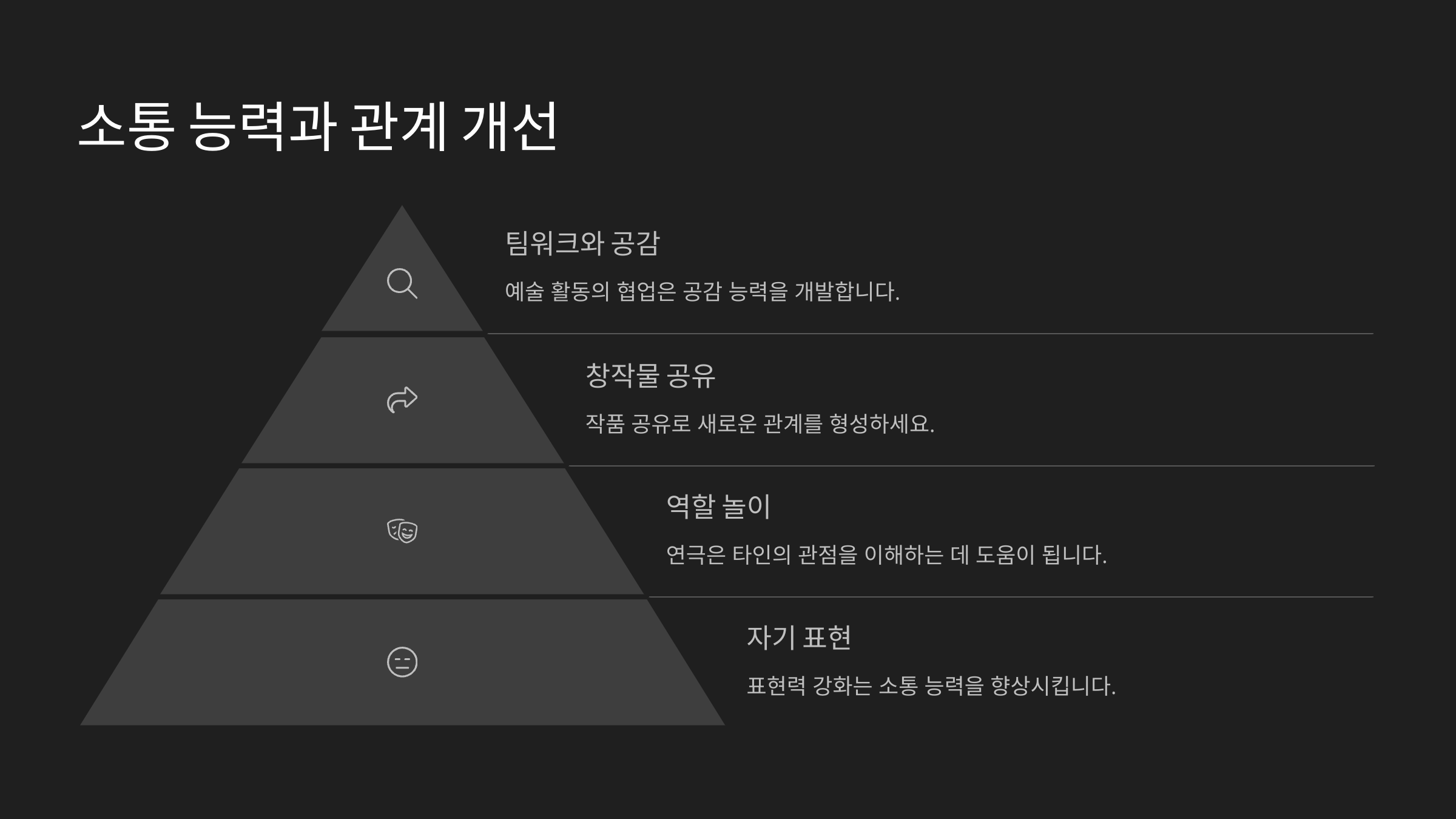
소통 능력과 관계 개선
디지털 메시지가 넘쳐나는 요즘, 손글씨로 전하는 메시지는 그 자체로 감동이에요. 제가 친구 생일에 손글씨로 편지를 써줬을 때, 받는 사람이 눈물까지 글썽였던 기억이 있어요. 그 사람을 생각하며 하나하나 정성스럽게 쓴 글씨는 진심이 고스란히 전해지거든요.직접 쓴 글귀는 사람과의 거리도 좁혀줘요. 예를 들어, 부모님께 '고마워요'라는 문장을 써서 작은 액자에 담아 드렸는데, 평소보다 훨씬 더 진심이 전해졌다고 하시더라고요. 캘리그라피는 마음을 시각적으로 표현하는 언어예요.
소셜미디어에도 자주 활용돼요. 직접 쓴 감성 문장을 사진과 함께 올리면 사람들과 감정적으로 소통할 수 있어요. 단순히 좋아요 수를 넘어서, 마음이 연결되는 순간들이 생겨요.
더불어 직장에서의 커뮤니케이션에도 활용할 수 있어요. 손글씨 메모나 작은 메시지 하나로 분위기를 따뜻하게 만들 수 있답니다. 감성은 디지털보다 오래 기억되는 법이니까요.
💌 감성 캘리그라피 사용 예
상황 사용 문장 전달 감정 받는 이 반응 생일 선물 "세상에 단 하나뿐인 너" 감동, 고마움 감격, 눈물 부모님 감사 "언제나 든든한 존재" 사랑, 존경 미소, 안도 퇴사 동료 "같이여서 행복했어요" 추억, 감사 감사 메시지 이처럼 손글씨는 단순한 표현을 넘어서, 사람의 마음을 움직이는 힘이 있어요. 진심을 담은 글씨가 관계를 더 가깝게 만들어준답니다. ✨
💼 취미를 넘어 수익으로
취미를 넘어 수익으로 처음엔 나를 위한 힐링으로 시작한 캘리그라피가 어느새 누군가에게 필요한 작업이 되기도 해요. 점점 실력이 늘다 보니 주변에서 부탁이 들어오기 시작했어요. 카드, 포스터, 현수막, 가게 간판까지 다양하게 활용되거든요.
요즘은 캘리그라피로 부업을 시작하는 사람들도 많아요. SNS에 작품을 올리거나, 온라인 클래스 플랫폼에서 강사로도 활동할 수 있어요. 또는 캘리그라피를 활용한 문구 제품을 직접 제작해 판매하기도 하죠.
특히 결혼식 초대장이나 기업 행사에도 손글씨가 큰 역할을 해요. 디지털 디자인과는 다른 ‘감성’이 있기 때문에 점점 수요도 높아지고 있어요. 자신만의 스타일이 확고해지면 브랜드화도 가능하답니다.
경제적 가치뿐만 아니라 성취감도 커요. 내가 쓴 글씨가 누군가에게 기쁨이 되고, 작품이 되어 누군가의 공간에 놓인다는 건 정말 뿌듯한 일이에요.
📈 캘리그라피 수익화 경로
수익 활동 설명 시작 방법 클래스 운영 취미 강좌나 원데이 클래스 SNS 홍보 + 클래스101 등 상품 제작 엽서, 포스터, 손글씨 굿즈 쿠팡, 스마트스토어 기업 콜라보 광고 문구 디자인 포트폴리오 발송 나만의 취미가 하나의 작품이 되고, 누군가에게 가치를 주는 일이 된다는 건 정말 멋진 일이에요. 캘리그라피, 진심으로 추천하고 싶어요! 😊
Q1. 캘리그라피를 처음 시작하려면 어떤 도구가 필요한가요?A1. 기본적으로 붓펜, 연습용 종이, 가이드북 하나면 충분해요. 천천히 시작하는 게 중요하답니다!
Q2. 혼자서 독학해도 잘 배울 수 있나요?
A2. 요즘 유튜브, 블로그, 온라인 강의가 잘 돼 있어서 충분히 가능해요. 중요한 건 꾸준함이에요 😊
Q3. 캘리그라피에 재능이 꼭 있어야 하나요?
A3. 아니에요! 글씨체는 연습할수록 좋아져요. 감정을 담는 게 더 중요하답니다.
Q4. 손글씨가 원래 안 예쁜데, 잘 할 수 있을까요?
A4. 정자체가 아니라도 괜찮아요. 나만의 개성 있는 글씨가 되니까 너무 걱정하지 마세요!
Q5. 캘리그라피는 얼마나 자주 연습해야 하나요?
A5. 하루 10~15분이라도 꾸준히 해보세요. 일주일만 해도 손에 감이 와요!
Q6. 수익을 내려면 어느 정도 실력이 되어야 하나요?
A6. 글씨의 완성도보다, 전달력과 감성이 중요해요. 포트폴리오 몇 개만 잘 만들어도 시작할 수 있어요.
Q7. 디지털 캘리그라피와 손글씨의 차이는 뭔가요?
A7. 디지털은 수정이 편리하고, 손글씨는 감성과 감촉이 살아있어요. 둘 다 각각의 매력이 있죠!
Q8. 캘리그라피를 배우면 어디에 활용할 수 있나요?
A8. 초대장, 선물, 인테리어, 상품 패키지, SNS 등 정말 다양해요. 활용도는 무궁무진하답니다!